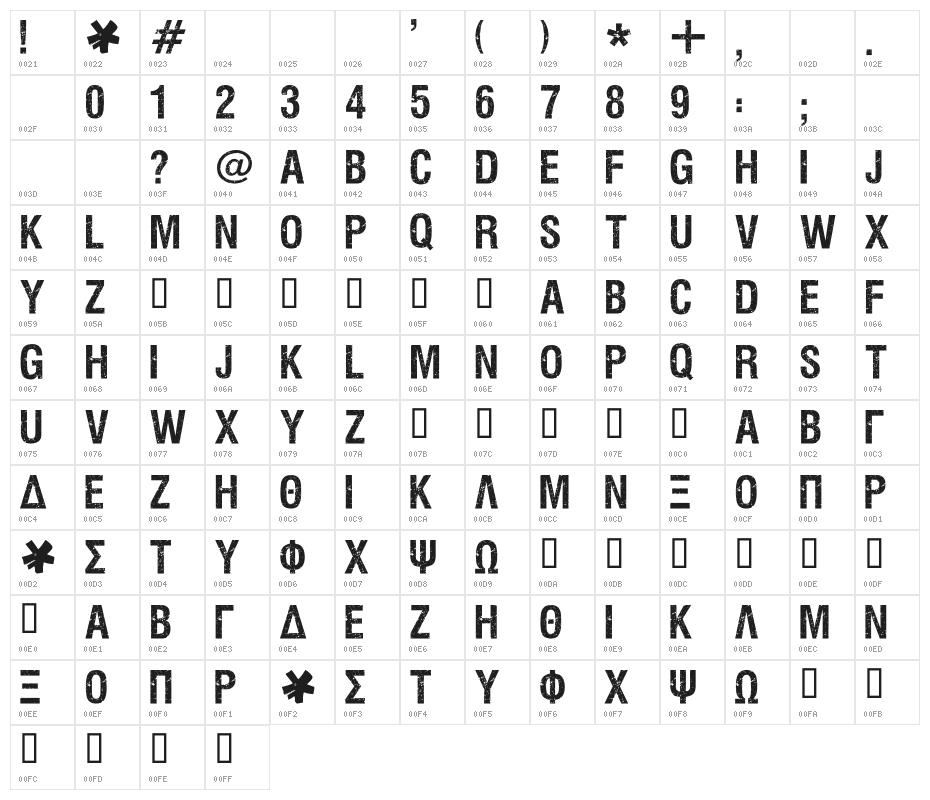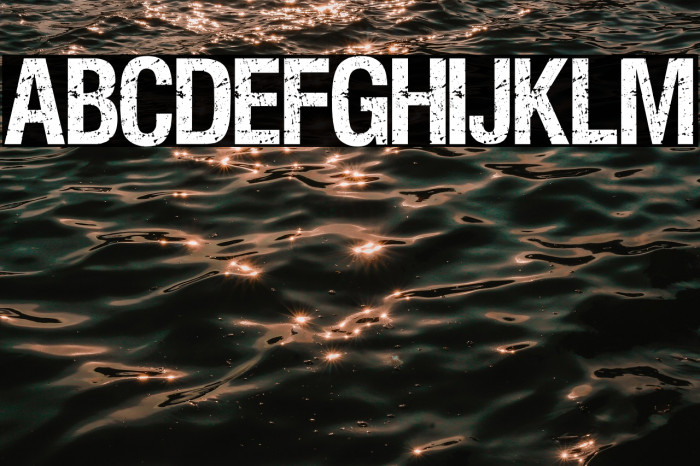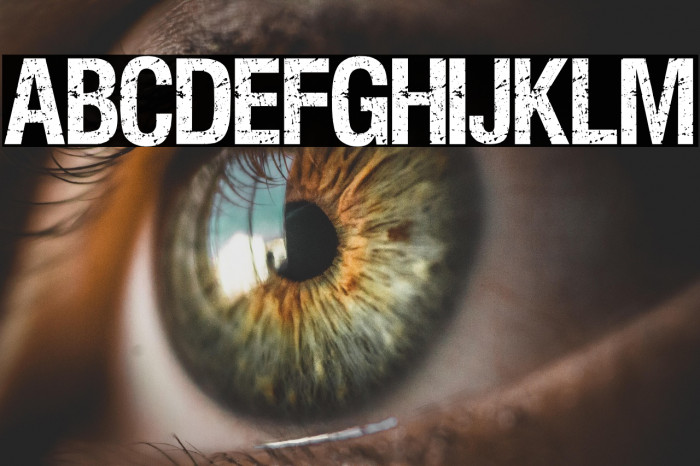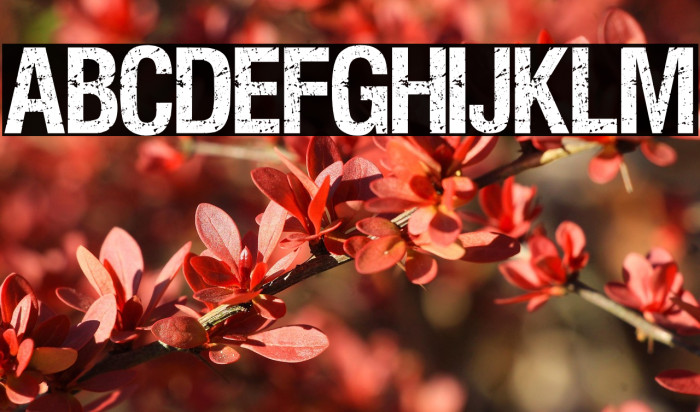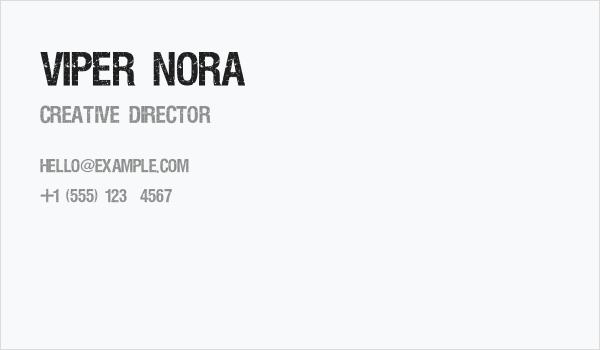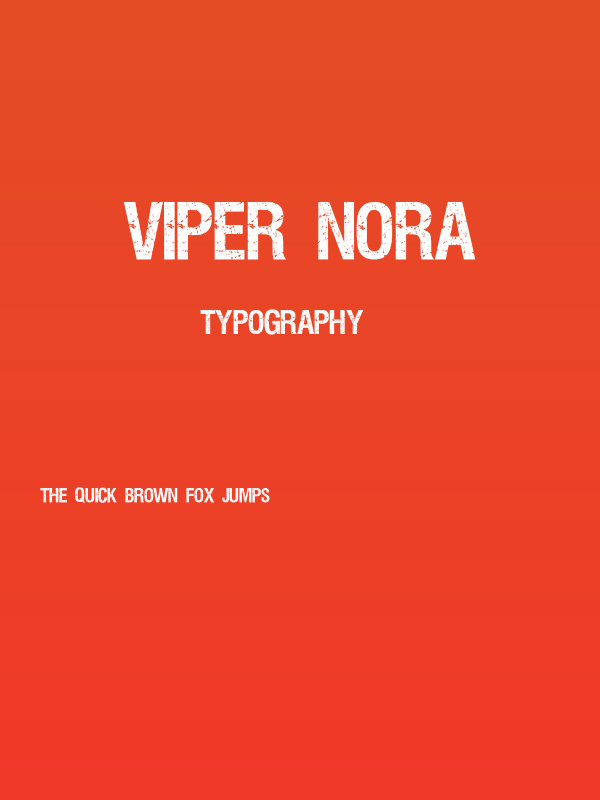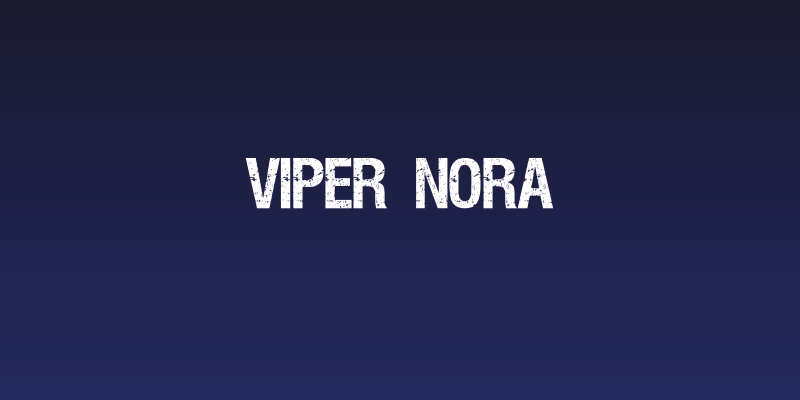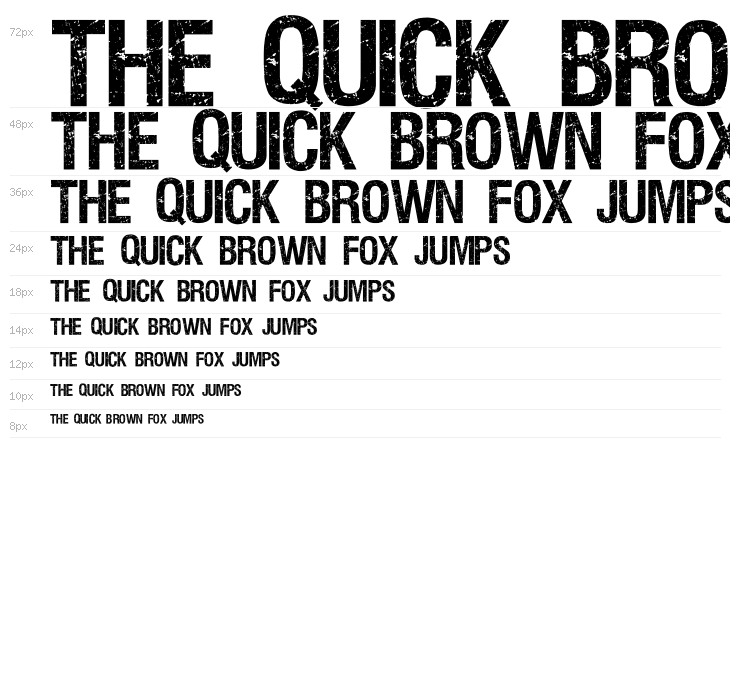
VIPER NORA Font
✎ Messy
| Progetti proposti | Ideal for posters, album covers, branding for outdoor or adventure products, and any design needing a strong, vintage feel. |